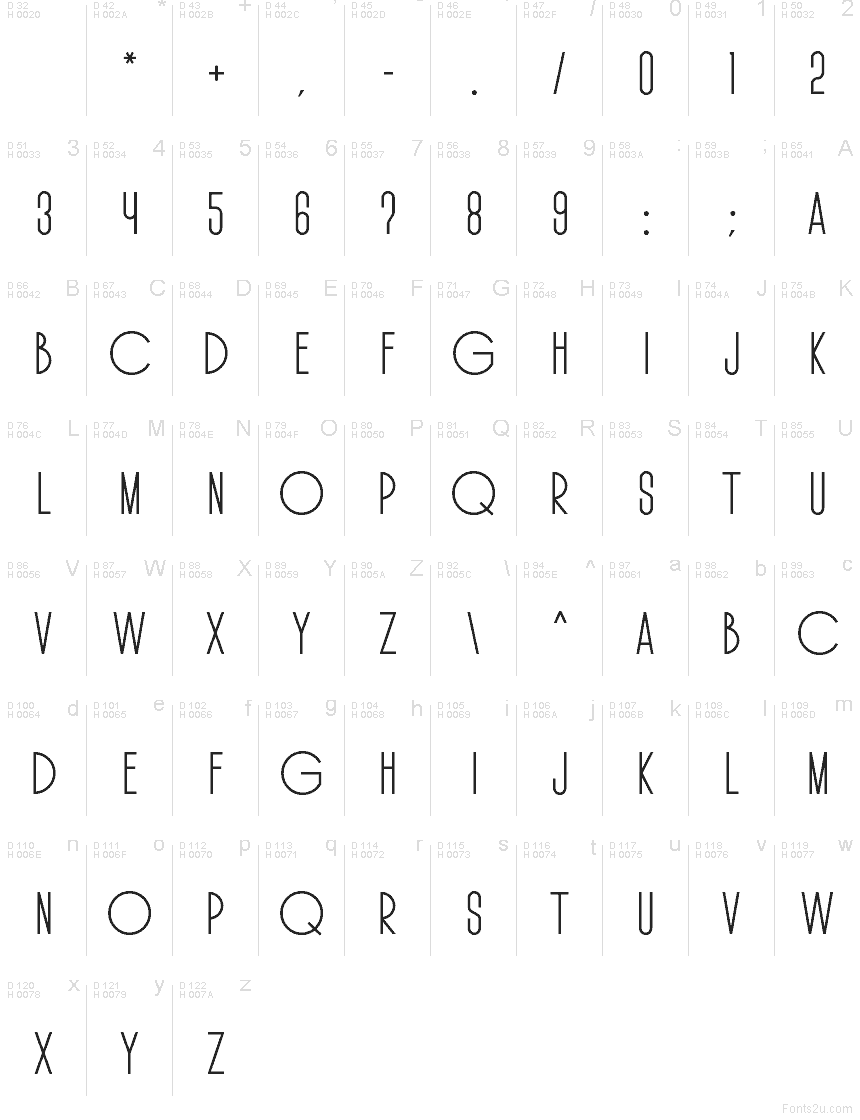
Gonela Regular di Afkari Studio è un font sans serif geometrico gratuito con un'estetica elegante che richiama l'Art Déco. Le lettere abbinano cerchi quasi perfetti a tratti lunghi ed essenziali, conferendo al font un carattere architettonico e arioso, ben lontano dalla neutralità; il ritmo calmo nasce dalla ripetizione di forme arrotondate e da una spaziatura molto aperta.
Si presta perfettamente al branding di moda, alle testate di riviste, ai poster di gallerie, al packaging e alle titolazioni dove un tocco di sobrietà fa la differenza. Come font gratuito, Gonela dà il meglio di sé in contesti espositivi brevi, monogrammi e copertine: quei cerchi ampi e le lettere alte ed essenziali donano anche a poche parole una presenza deliberata e armoniosa.